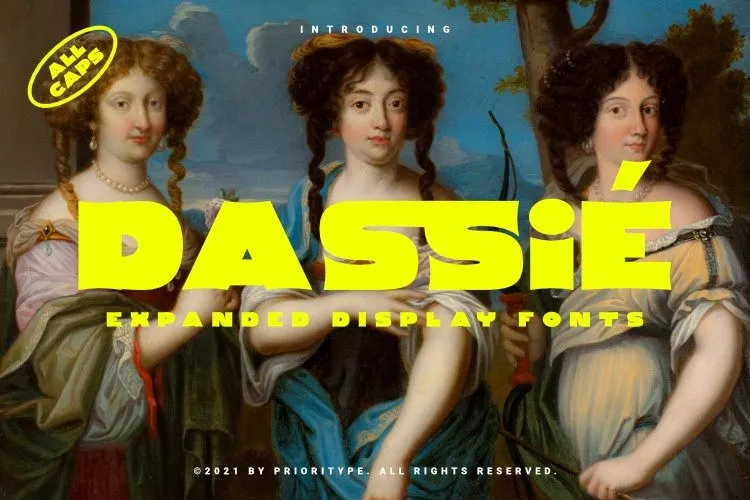
Dassie Display Font é uma fonte serif bold que destaca-se pela sua personalidade inovadora e alegre, ideal para design de apelo ao público jovem. Com seu toque retrô moderno, você pode adaptá-la a diversas tipografias, desde criações de camisetas até projetos promocionais ou conteúdo online. Suas linhas arredondadas e detalhes sutis criam um contraste encantador entre o clássico e o atual, tornando-a perfeita para estilos que buscam uma conexão com a história. Teste alguns dos modelos de pré-vizualização acima para sentir o poder deste fonte em seus projetos. Estamos ansiosos para vê-lo em ação!